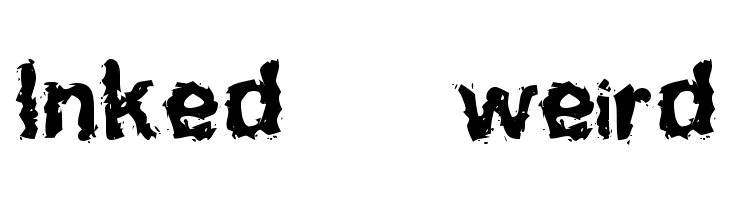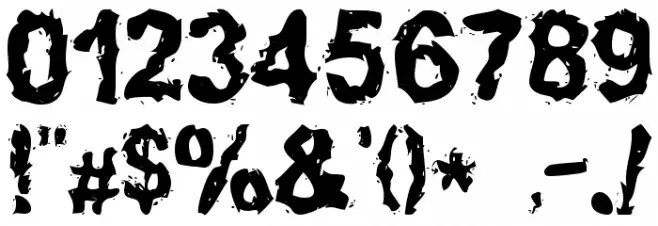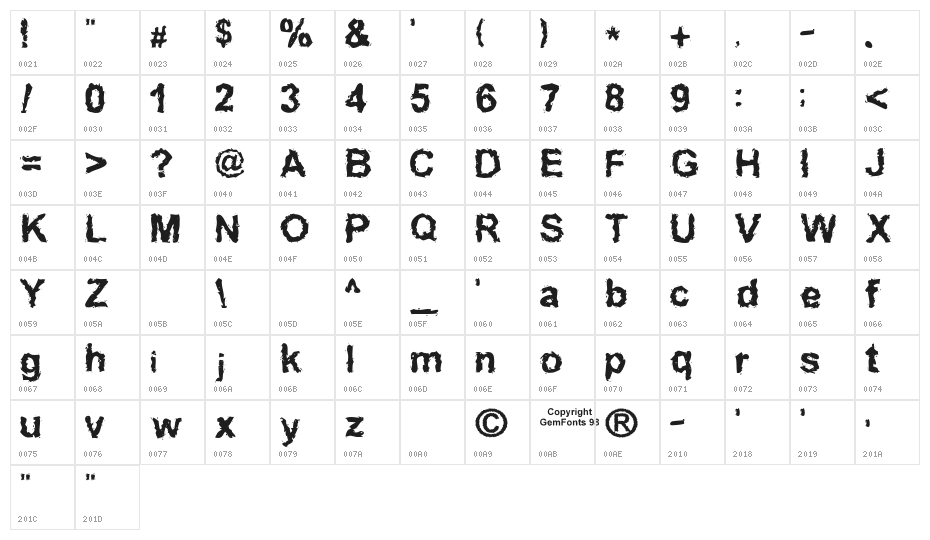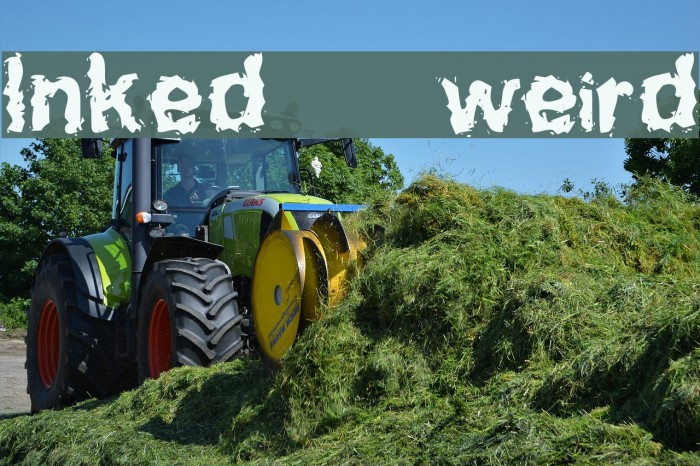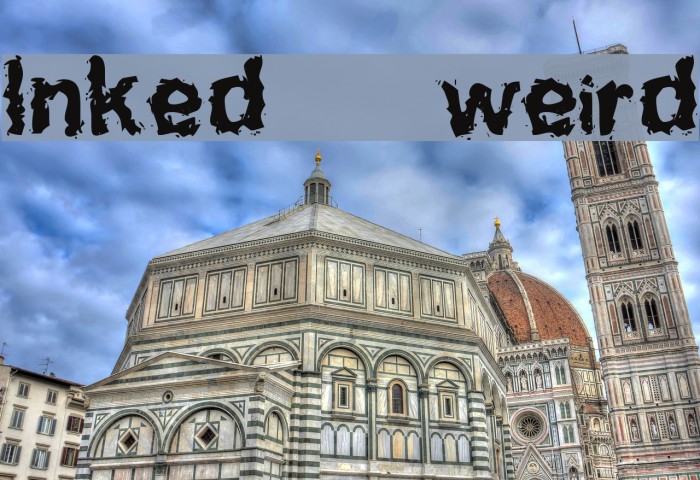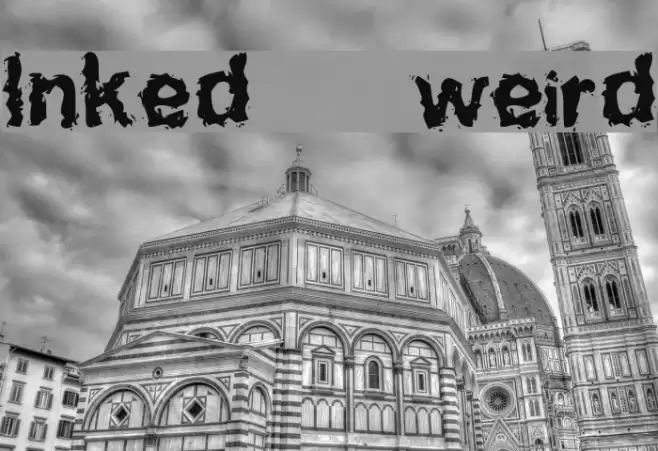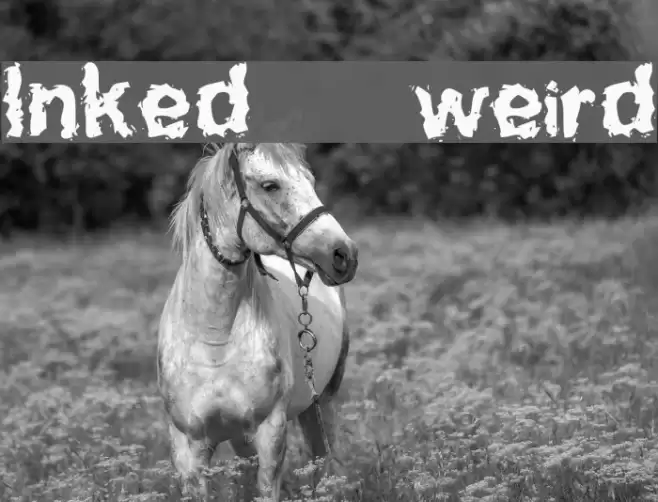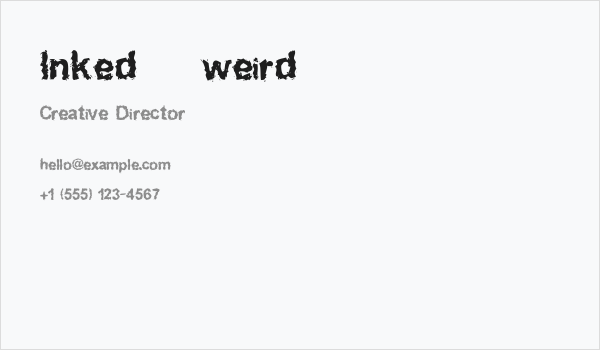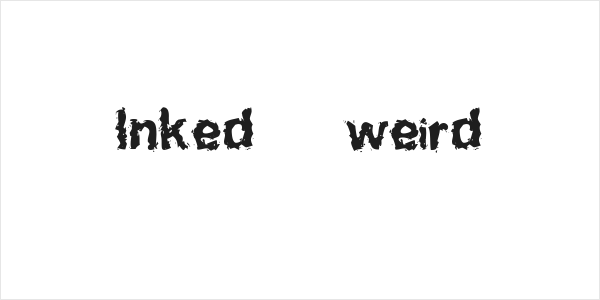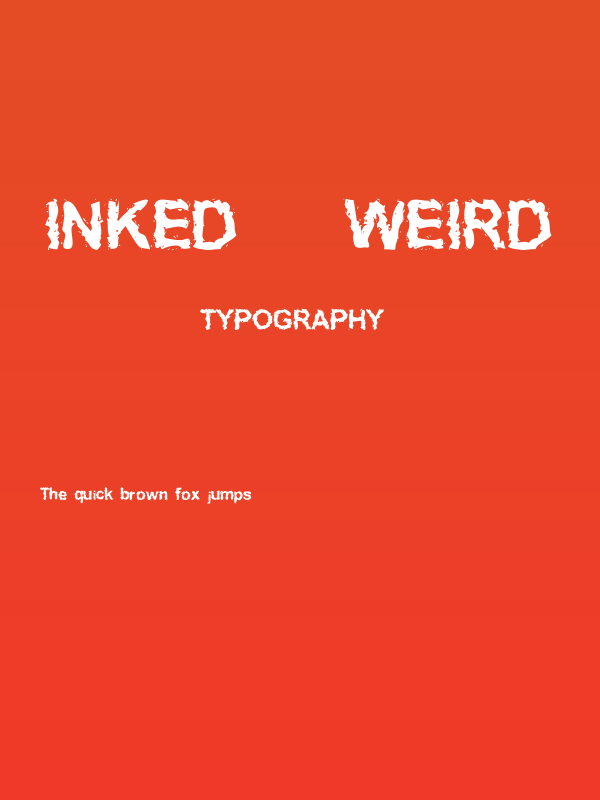
Inked weird Font
✎ Distorted Eroded
| Catégories | Distorted Eroded |
| Style général | Grunge, Edgy |
| Cas d'utilisation | Headlines, Posters, Logos |
| Projets proposés | Ideal for music album covers, edgy posters, or rebellious branding. |